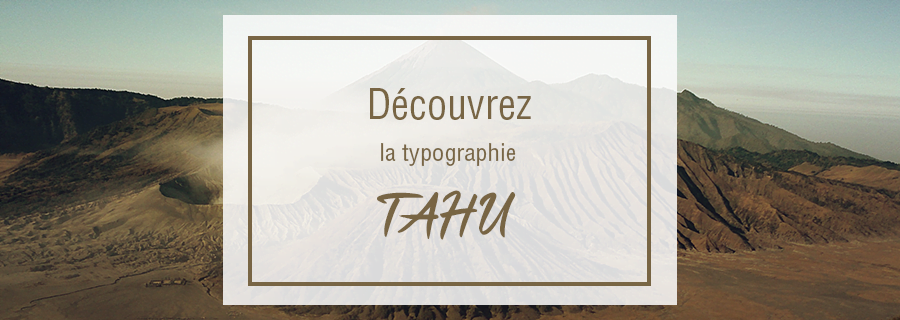
Stanburghe : la typographie qui rajeunit la calligraphie
Electronica : la typographie des événements musicaux
La typographie Nozty : quand le passé se conjugue au présent
Splash : la typographie qui fait tâche
Peut-être que son drôle de nom nous en dit déjà long sur . Dès le premier coup d’oeil, il est évident que typographie Splash ne fait pas dans le règlementaire. Elle nous éclabousse par son allure détonnante. Simple par ses caractères en majuscule, elle vient ajouter sa tâche de créativité en faisant pleuvoir quelques fragments de peinture par-ci par-là.
Forests Layered, une typographie grandeur nature
Venez vous perdre dans la nature sauvage suggérée par la typographie Forests Layered, designé par Zeppelin Graphics. Cette police, que l’on se figure déjà sentir un doux parfum boisé, fera souffler un vent de fraîcheur sur votre communication.
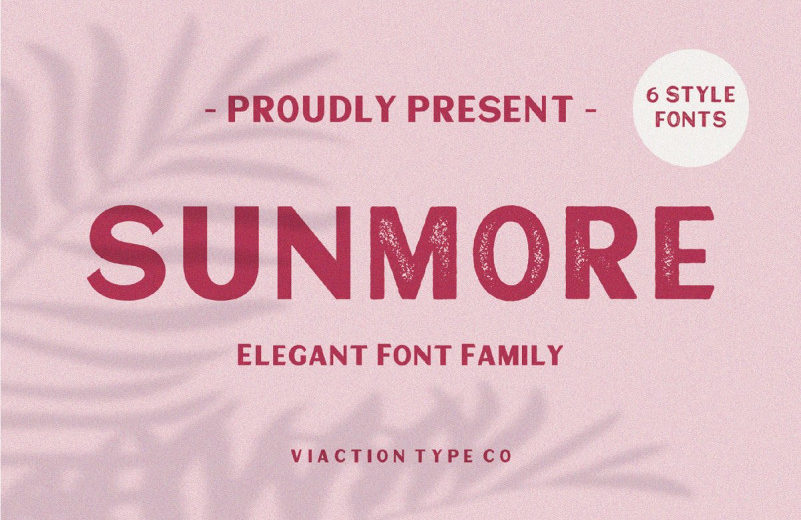
Sunmore : la typographie entre vintage et modernité
À la recherche d’une famille de police à la fois actuelle et old school, nous vous avons déniché le bon filon. Sunmore, c’est une typographie aux caractères élégants et dont le nom et le style graphique unique nous font voyager jusque dans les années 80, aux abords d’une plage californienne.
Aerioz : une typographie toute en légèreté
Fluide, légère, aérienne, élancée… Les adjectifs ne manquent pas pour qualifier la typograhie Aerioz. Dessinés en monoligne, les traits de chaque caractère s’entrelacent à la perfection pour former des mots à l’aspect lisse et élégant.
King’s Gambit : La typographie souveraine
King’s Gambit fait souffler un vent d’élégance et de mondanité au royaume de la typographie. Le style graphique singulier de cette police d’écriture créée par Matthew Welch se base sur un jeu visuel étonnant. Les parties les plus fines des caractères ont été effacées au profit des plus denses, si bien que l’oeil distingue parfaitement chaque lettre bien qu’une partie soit manquante.
Nordic : une typographie de caractère
Replongez au plus profond de l’ère Viking avec la typographie Nordic ! Inspirée des anciennes runes scandinaves, Nordic remet au goût du jour le système d’écriture d’un peuple qui fascine en donnant à chaque lettre un design et une géométrie unique.
Nouvelle typographie gratuite : LORA !
Berg : typographie gratuite
Berg est une famille de polices multicouche de Brosnes. Inspiré de la peinture, des affiches et des étiquettes d’époque, Berg propose des formes fortes qui attirent particulièrement l’attention.
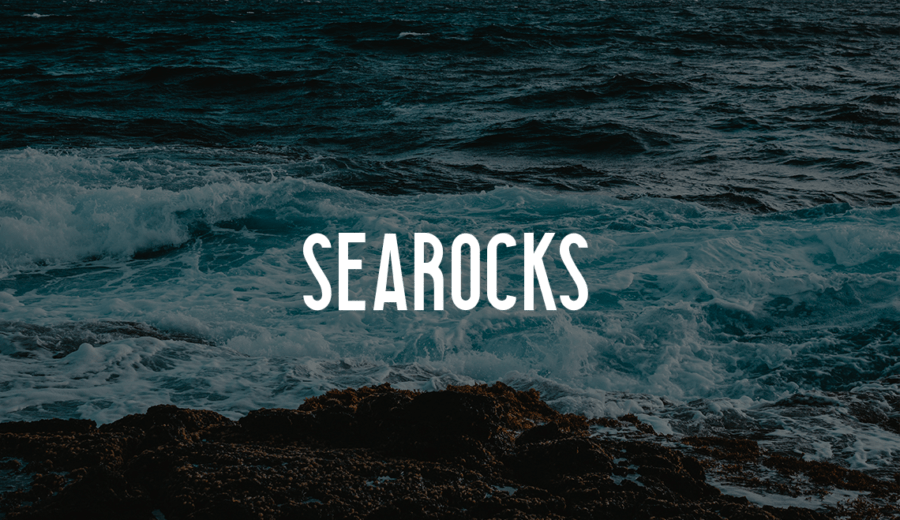
Typographie gratuite : Searocks !
Voici la typographie Searocks. Une police de caractères polyvalente condensée sans empattement réalisée par Roman Paslavskiy.
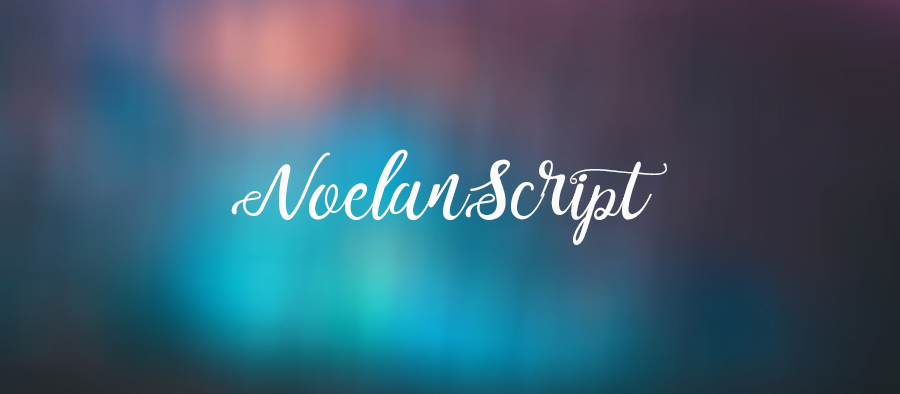
NOELAN SCRIPT : typographie gratuite
Noelan Script est une calligraphie inventée par Ndroadv. Au design très propre et moderne, cette typographie comprend des lettres capitales et des minuscules, des caractères numériques, mais également des symboles.
KINGSLAND : typographie gratuite
Rencontrez la nouvelle police manuscrite Kingsland de Makeitrock. Cette typographie présente les imperfections naturelles de l’écriture quotidienne.
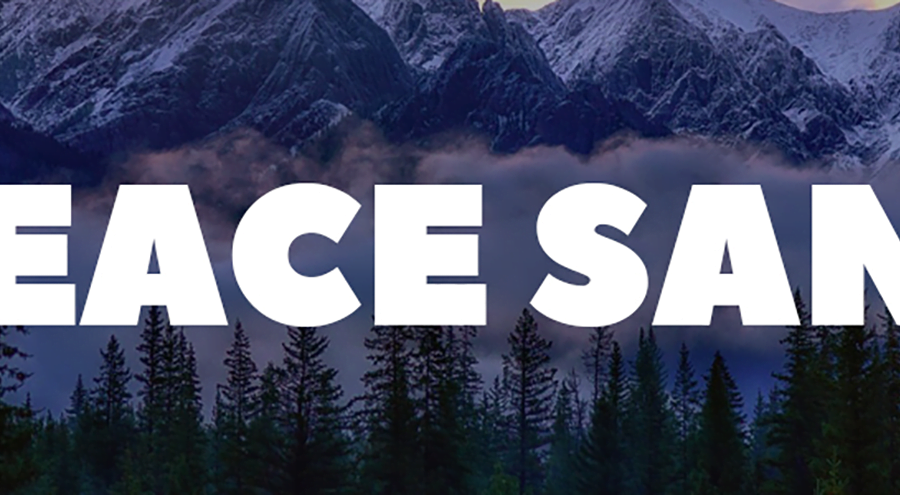
PEACE SANS : typographie gratuite
Découvrez sans plus attendre la typographie PEACE SANS. Améliorez vos créations graphiques grâce à cette police d’écriture bold réalisée par Sergey Ryadovy.
Typographie gratuite CUNIA !
Cunia est une police d’écriture sans serif aux coins légèrement arrondis conçu par Alejo Bergmann. Cette typo comprend : des majuscules, des minuscules ainsi que des caractères numériques et des symboles.
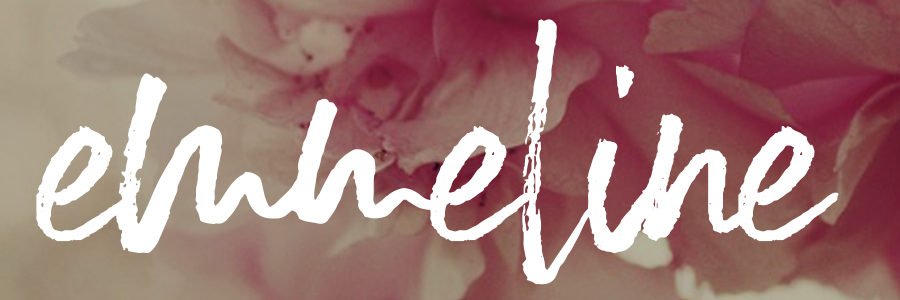
EMMELINE : typographie gratuite
Emmeline est une police d’écriture manuscrite gratuite réalisée par Sinikka Li qui comprend plus de 260 caractères.
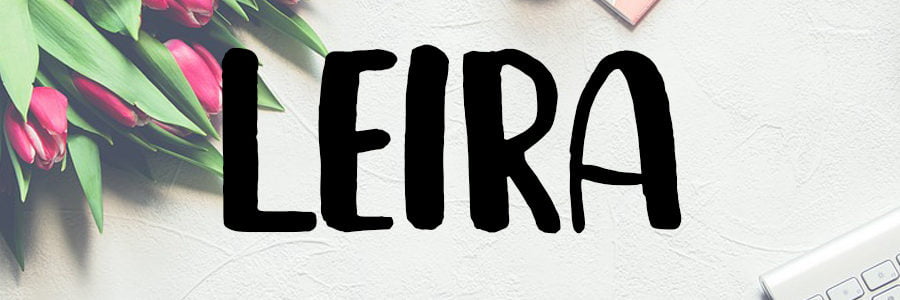
LEIRA : typographie gratuite !
On ne vous présente plus notre hebdomadaire #CESTCADEAU. Nous avons le plaisir de vous faire découvrir notre dernière trouvaille : LEIRA.
WESTFALIA : TYPOGRAPHIE GRATUITE
L’heure du traditionnel #CESTCADEAU #Typographie a sonné. Chez Exaprint, nous savons que vous êtes fans de ce rendez-vous hebdomadaire. Aujourd’hui, c’est la typo WESTFALIA qui est disponible en téléchargement gratuit.
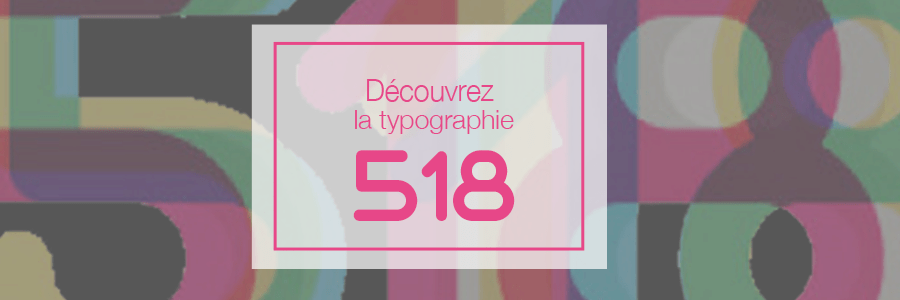
518 : typographie gratuite
Aujourd’hui, c’est une typographie made in France que nous souhaitons mettre en avant.
Chez Exaprint, nous vous avons trouvé une petite pépite : la 518.
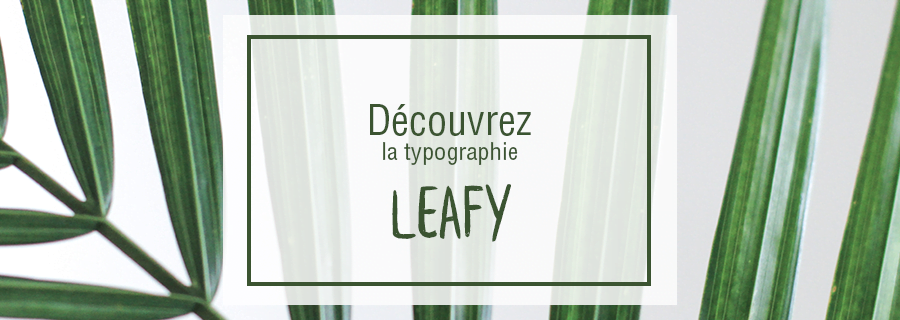
LEAFY : typographie gratuite !
Nous vous invitons à découvrir la typographie Leafy, réalisée par Ieva Mezule et Krisjanis Mezulis. Elle se compose de 95 caractères et des principaux signes de ponctuation.
MONA : typographie gratuite !
Pour le samedi #CESTCADEAU #TYPOGRAPHIE, nous vous proposons la typographie MONA : une police d’écriture manuscrite imaginée et dessinée par Evita Vilaka.
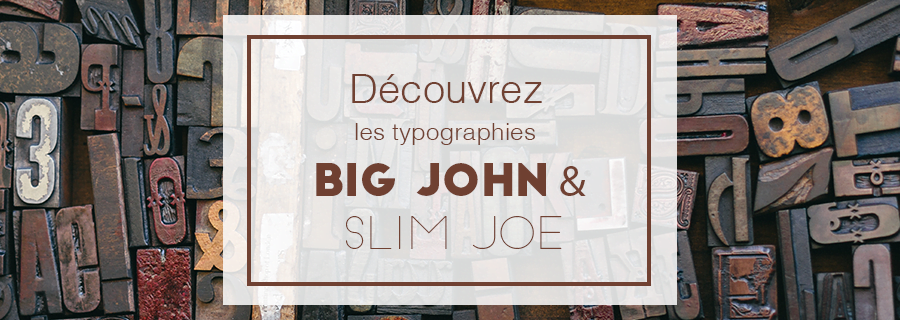
Typographie d’inspiration gothique : DemonLetter
Voici une typographie gratuite inspirée de l’univers gothique : la typo Demon. Parfaite pour des travaux originaux un peu « rock and roll », et sur différents supports comme : du packaging, des flyers ou du grand format.
Typographie : Ruby Ruby
La typographie Ruby Ruby est d’inspiration infantile et faite à la main, ce qui la rend parfaite pour des créations décontractées, sur des flyers par exemple.